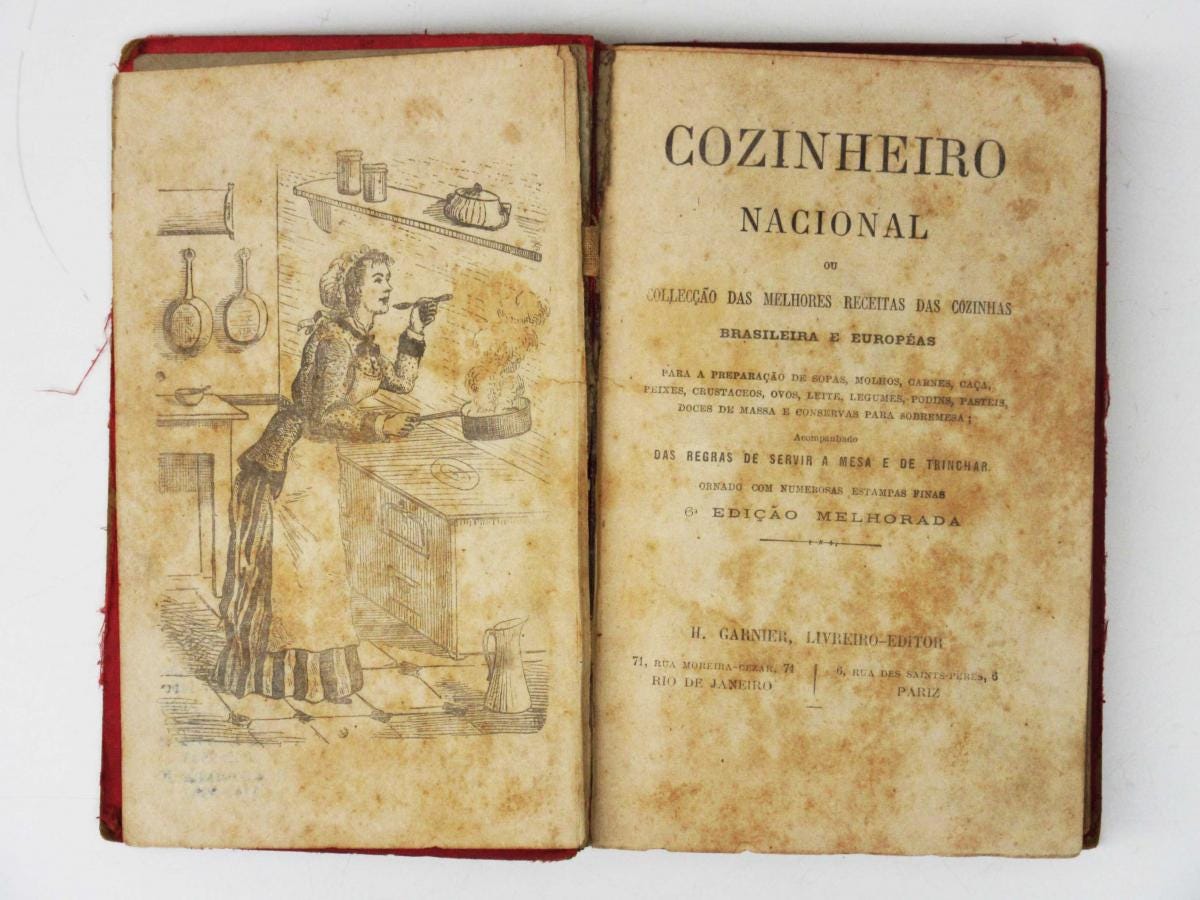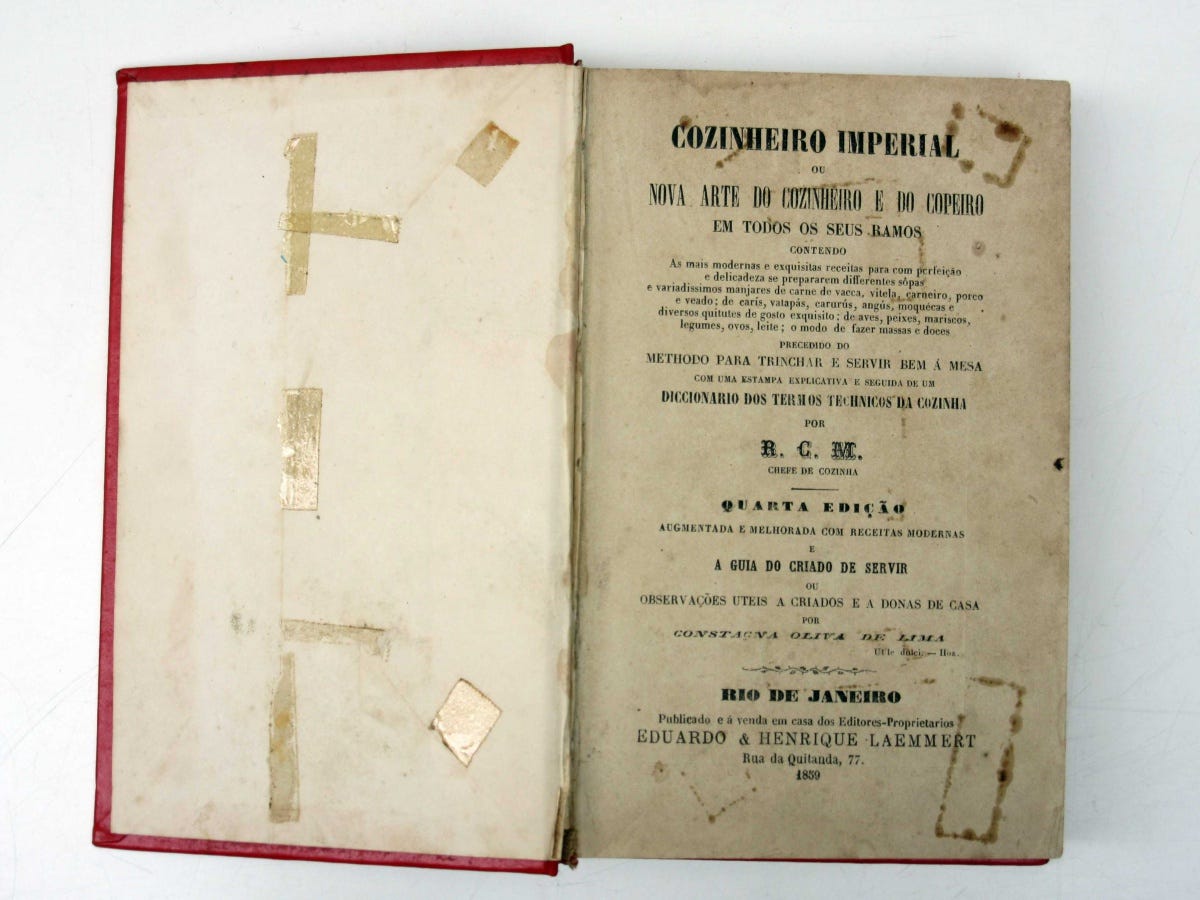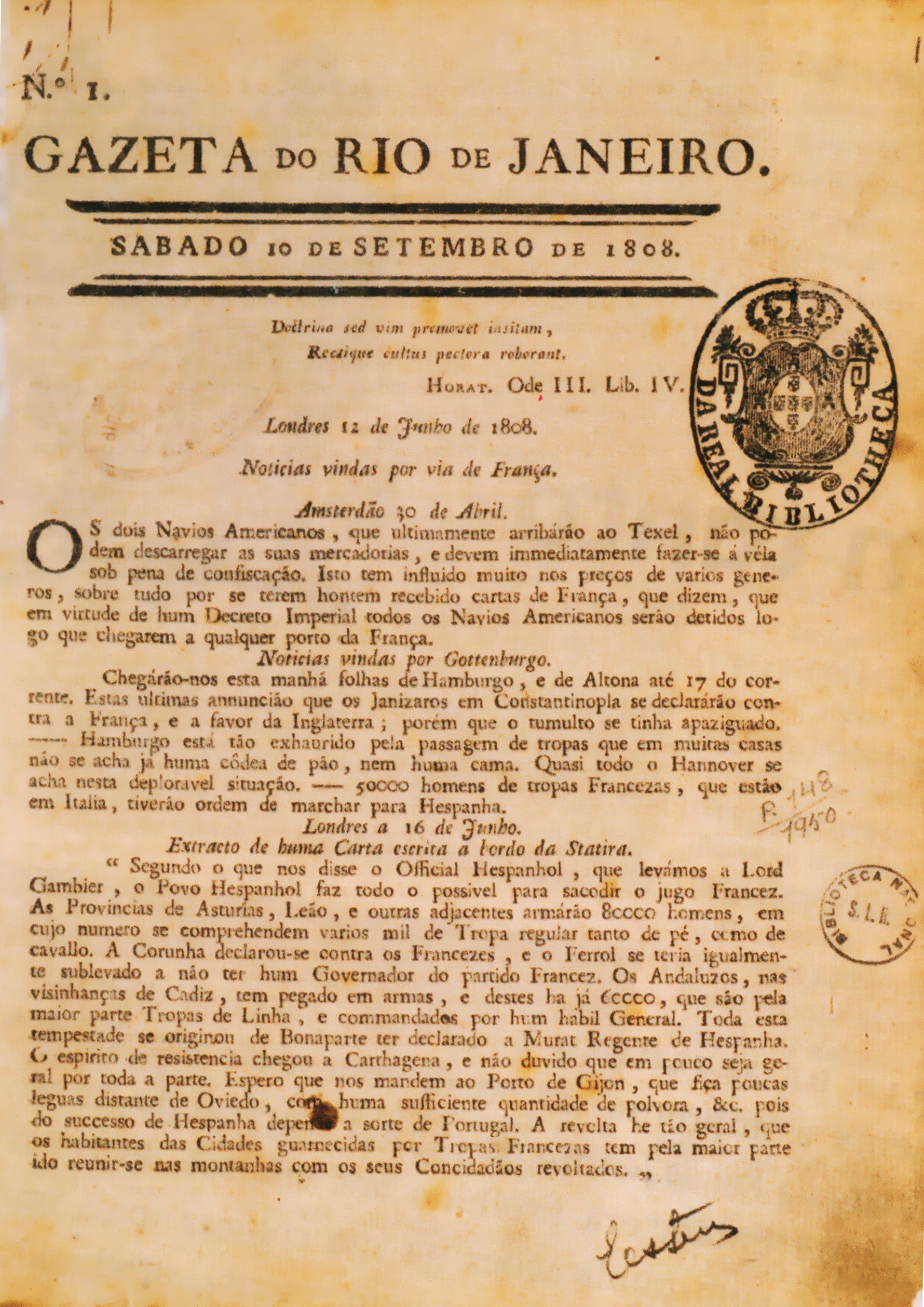
Tipo Aquilo #39 – O Cozinheiro Nacional
De vez em quando, eu gosto de usar esse canto aqui pra falar de livros antigos. Não apenas pelo lado tipográfico, de entender como era o uso dos tipos móveis e outros meios antigos de produção gráfica, mas também como uma maneira de entender melhor a sociedade da época desses livros. Hoje, essa edição dedica-se ao nascimento das duas grandes editoras brasileiras pós-independência, por meio de dois personagens: o Cozinheiro Imperial e o Cozinheiro Nacional, dois dos livros mais antigos de gastronomia do Brasil.
Há algumas semanas, falei aqui da expansão da tipografia pela América Latina e de como o Brasil chegou atrasado nesse processo. A proibição de atividades fabris durante o período colonial frustrou tentativas de produzir impressos em solo brasileiro, como a de Antônio Isidoro da Fonseca, e a demanda por livros e impressos era suprida exclusivamente por Portugal. Isso começou a mudar a partir de 1808, com a abertura comercial da colônia e a instalação em solo brasileiro da Biblioteca Real. Também chegaram o prelo, as caixas de tipos e as prensas que formariam a Imprensa Régia, detentora da exclusividade de impressão tipográfica no Brasil até 1821.
O processo de independência do Brasil foi movido por uma elite que havia enriquecido durante a presença da realeza no Brasil, que consumia livros importados da França e Inglaterra, mas tinha uma demanda latente por volumes impressos no Brasil. Essa elite fez nascer e prosperar, mais tarde, a Livraria Universal, fundada em 1833 pelo alemão Eduard Laemmert. O sucesso da livraria motivou Eduard a expandir a livraria para uma editora, junto com seu irmão Heinrich. Aprendeu o ofício de tipógrafo, trouxe três impressoras para o Brasil e, em 1838, fundou a Typographia Universal, impressora de vários dos livros mais antigos do Brasil, como os populares Almanaques Laemmert.
Em 1840, foi lançado o primeiro livro de gastronomia impresso no Brasil, o Cozinheiro Nacional ou Nova Arte do Cozinheiro e do Copeiro em Todos os Seus Ramos, assinado por um suposto cozinheiro da família imperial chamado apenas por suas iniciais, R.C.M. Suas receitas eram inspiradas em dois volumes portugueses antigos, A Arte da Cozinha de 1640, e Cozinheiro Moderno de 1780. No entanto, ele não trava-se apenas de um compêndio de receitas: apesar de estar focado em receitas vindas da Europa, o livro trazia também ilustrações de ingredientes especiais, informações sobre o modo certo de preparar ambientes para banquetes, medidas convertidas para unidades locais da época, para quê servia cada tipo de talher e louça, o roteiro correto de comidas a servir, e tudo que alguém precisava saber para orientar os serviçais — em maioria, analfabetos e escravizados.
Agregar essas informações em um volume único era comum para a época, à exemplo dos almanaques que buscavam condensar em volumes únicos todo tipo de curiosidades que pudessem. Os livros produzidos pela Typographia Universal, feita no Rio de Janeiro, precisava viajar para vários cantos do Brasil, a fim de atender às elites locais (burgueses e nobres) e projetar nelas os ideais de luxo e realeza da então capital do novo império brasileiro; por isso, agregavam todo o conhecimento possível num encadernado. O livro funcionava como um guia para tudo relacionado à cozinha. Embora as oficinas tipográficas começassem a aparecer pelo Brasil, poucas tinham a qualidade de impressão e encadernação da fábrica de livros dos irmãos Laemmert. A presença deste e outros livros numa casa era vista como um luxo.
A atenção à cozinha local começou com a publicação de A Doceira Brazileira, em 1850, também pela Typographia Universal. O livro de autoria de Anna Maria das Virgens e Constança Oliva de Lima reforçava a tradição feminina da confeitaria, mas começava a incorporar receitas trazidas pela população africana escravizada. Essa tendência consolidou-se com o terceiro livro brasileiro de gastronomia, Cozinheiro Nacional ou Collecção das Melhores Receitas das Cozinhas Brasileira e Europêas para a preparação de sopas, molhos, carnes, caça, peixes, crustáceos, ovos, legumes, pudins, pastéis, doces de massa e conservas para sobremesa; acompanhado das regras de servir a mesa e de trinchar.
O concorrente foi lançado entre 1860 e 1870 pela Garnier, outra livraria nacional nascida após a independência. Diferente dos irmãos Laemmert, a editora de Baptiste Louis Garnier concentrava sua produção em Paris e Londres, imprimindo nesses lugares livros de vários autores brasileiros, como Olavo Bilac, Joaquim Nabuco e um certo Machado de Assis. O Cozinheiro Nacional era impresso na França, mas trazia diversas receitas comuns na gastronomia brasileira, influenciada pela população indígena e africana. Seu sucesso comercial motivou os irmãos Laemmert a adicionar receitas nacionais nas edições seguintes do Cozinheiro Imperial; algumas dessas adições foram feitas pela própria Constança, do Doceira Brazileira.
Assim como seu concorrente, o Cozinheiro Nacional funcionava como um almanaque de conhecimentos consoantes à cozinha, trazendo desde as receitas aos modos à mesa, instruções de refeição, como gelar bebidas, e até elixires caseiros para aliviar dores e desconfortos. Outro destaque do Cozinheiro Nacional era um guia de substituição de ingredientes, que auxilia o cozinheiro a produzir no Brasil receitas com insumos indisponíveis no país. Algumas dessas substituições são curiosas: a recomendação de usar chuchu ou abóbora d’água ao invés de pepino, abóbora no lugar de cenoura e tomates no lugar de uvas desperta curiosidade sobre porque esses ingredientes comuns na nossa cozinha atual eram descritos como incomuns, e um breve perfil da dieta dessa sociedade.
Outra peculiaridade desses livros é que as receitas tinham poucas indicações de quantidade. Entendia-se que os leitores já tinham noções prévias de cozinha antes de aventurar-se pelas receitas, ou que as receitas não demandavam medidas exatas por serem transmitidas oralmente entre gerações. Quanto tempo a sua geléia de galinha (não me pergunte) precisava assar no forno à lenha? Só os experientes sabem. O toque final de sabor ficava à cargo do cozinheiro, que contava com sua intuição para garantir uma boa refeição para grandes banquetes e também jantares íntimos de… 12 pessoas. Numa sociedade sem restrições de procriação, os núcleos familiares eram muito maiores que os atuais.
As editoras dos Laemmert e de Garnier foram as grandes livrarias dos primeiros anos do Brasil Império; no período em que seus fundadores estavam vivos, as duas editoras foram as grandes impressoras e vendedoras de livros da elite brasileira. Além dos livros de cozinha, os Almanaques Laemmert eram grandes sucessos de venda e importantes registros da vida cotidiana brasileira, sendo até hoje registros importantes para o estudo da economia e sociedade da época. A Garnier, por sua vez, foi uma grande tradutora de volumes antes disponíveis apenas em francês, além de popularizar grandes autores brasileiros e os formatos franceses in-oitavo e in-doze de livros. As duas ajudaram, enfim, a colocar o Brasil como um pólo de produção editorial. Fomentaram o começo da produção tipográfica no país, ainda que numa escala muito pequena, com desenhos de letras e ornamentos vindos de fora feitos por pequenas fundições, como a Henrique Rosa.
Recomendações:
🎧 Podcast: Pastelando #12, com Leticia Dáquer, Meg Ganciné, Guilherme Atêncio e Tupá Guerra discutindo sobre os dois livros e os costumes culinários do Brasil pós-colônia.